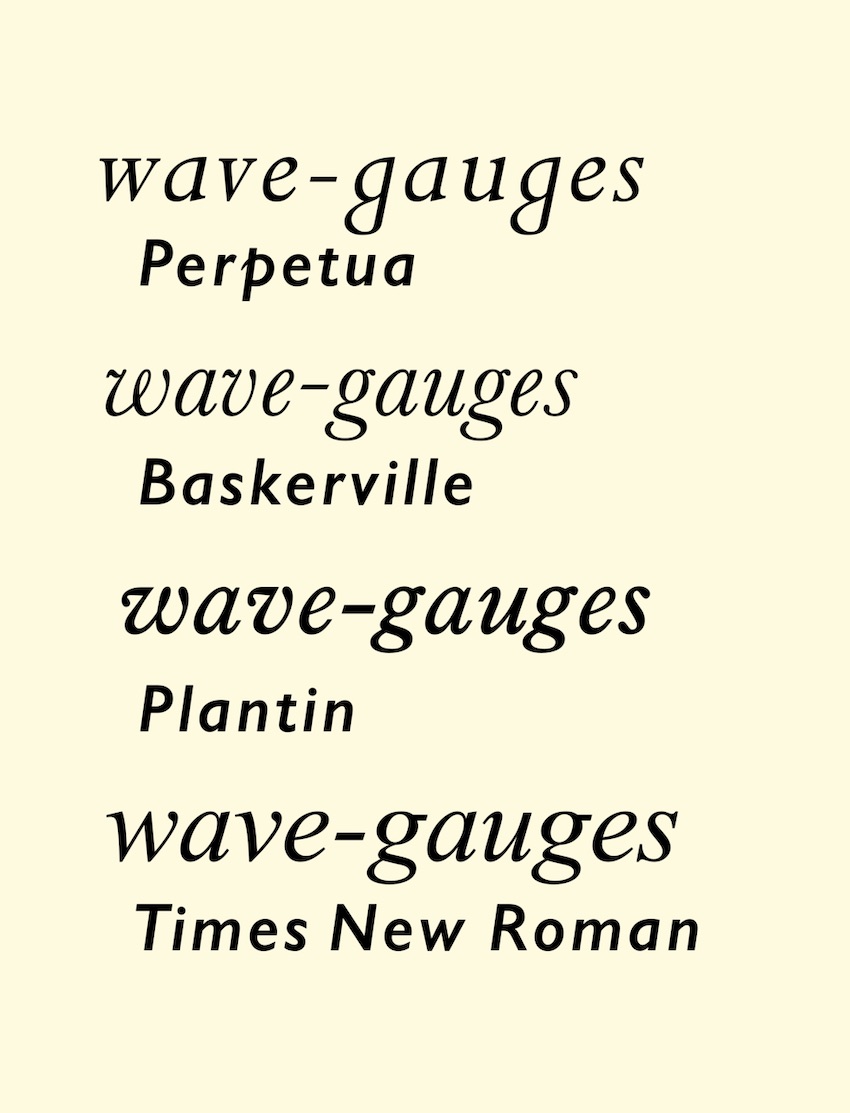
Шрифт Times New Roman: история и причины популярности
Популярность шрифтов, подобных Times New Roman, растет, и легко понять, почему. Классическое семейство шрифтов Times New Roman используется повсюду, от газет до популярного программного обеспечения, и теперь оно стало мгновенно узнаваемым.
Но то, что Times New Roman хорошо знакомо означает, что он стал чем-то вроде заурядного дизайнерского выбора. Вариант по умолчанию, но кому это нужно?
Выбирая шрифт, который содержит определенные черты Times New Roman, но также имеет собственную индивидуальность, вы получаете лучшее из обоих миров: классический стиль с современными нотками.
В этой статье мы рассмотрим шрифты, похожие на Times New Roman. Но сначала давайте коротко узнаем историю самого Times New Roman.
История Times New Roman
Семейство шрифтов Times New Roman сегодня встречается повсюду, но с чего все это началось? Впервые шрифт появился в британской газете The Times 3 октября 1932 года.
The Times поручила годом ранее полиграфической компании Monotype изменить дизайн шрифта, а дизайнер Стэнли Морисон рекомендовал более солидный и современный дизайн для замены своего предшественника 19 века. Он использовал шрифты Perpetua, Baskerville и Plantin в качестве вдохновения, но внес существенные изменения, чтобы создать уникальный шрифт, который выдержит испытание временем.
The Times продолжали использовать Times New Roman еще 40 лет, прежде чем в 1972 году придумали новый дизайн и с тех пор было еще несколько изменений. Все новые шрифты по-прежнему основаны на оригинальном дизайне Times New Roman Морисона.
С 1972 года семейство шрифтов Times New Roman начало жить собственной жизнью, получив известность далеко за пределами газетного мира. В первые дни Интернета веб-сайты могли использовать только несколько шрифтов, и Times New Roman был одним из них. Посмотрите на веб-сайт 1997 года, и, скорее всего, он использует Times New Roman.
Times New Roman также был шрифтом по умолчанию в Microsoft Word в течение многих лет, а Word был программным обеспечением по умолчанию для всех, кто создавал документы в те дни. Так Times New Roman стал стандартом для всего, от юридических документов до школьных сочинений. Это было повсюду.
В настоящее время, когда доступно так много различных вариантов, Times New Roman не так доминирует, как раньше. В наши дни дизайнеры часто уклоняются от него, считая, что это слишком примитивно, слишком скучно. И все же вы все равно увидите, что он появляется в документах и на веб-сайтах и, как вы узнаете позже в этой статье, есть несколько отличных альтернатив Times New Roman, которые можно взять, чтобы использовать его классическую привлекательность при создании дизайна со своей индивидуальностью.
Характеристики Times New Roman
Есть вопросы о семействе шрифтов Times New Roman? Вот несколько ответов на распространенные вопросы об этом популярном шрифте.
Какой тип шрифта Times New Roman?
Times New Roman — это шрифт с засечками, разработанный для хорошей читабельности в плотных газетных столбцах. Он довольно сжатый, имеет большую высоту по оси Х и короткие нижние выносные элементы. Все это позволяет легко читать даже при небольшом размере и в плотных столбцах текста.
Times New Roman — это шрифт с засечками?
Да. Он классифицируется как переходный шрифт с засечками, что означает, что он находится между старым и современным.
Times New Roman - моноширинный шрифт?
Нет. Times New Roman — это пропорциональный шрифт или шрифт переменной ширины. В моноширинных шрифтах все символы имеют одинаковую ширину — они были обычным явлением во времена пишущих машинок и на заре компьютерного кодирования. Как правило, шрифты переменной ширины, такие как Times New Roman, приятны для глаз.
Вопрос мог возникнуть, потому что Times New Roman была создана компанией Monotype. Но название не имеет ничего общего с моноширинными шрифтами.
Какие шрифты похожи на Times New Roman?
Хороший вопрос! В следующем разделе мы рассмотрим несколько примеров шрифтов Times New Roman, так что читайте дальше.
Шрифты, похожие на Times New Roman
Times New Roman — потрясающий шрифт, но на данный момент им немного злоупотребляют. Что, если вы хотите чего-то похожего, но с небольшими изменениями? Вот несколько шрифтов, как Times New Roman, которые можно попробовать.
Naia - изысканный шрифт с засечками
В этом сложном шрифте с засечками видно влияние Times New Roman, но он также имеет собственный особый стиль. Naia включает в себя все латинские символы (включая знак ударения), а также числа, специальные символы и знаки препинания. Полужирный шрифт будет отличной заменой для Times New Roman Bold.
Семейство шрифтов Sharis Serif
Шрифт Sharis Serif включает в себя некоторые черты Times New Roman, что делает его отличным для текста, где важна высокая степень разборчивости. Однако он не такой сжатый, как буквы Times New Roman, а семь различных весов позволяют создавать самые разные эффекты.
Thomas Craft: современный шрифт с засечками
Этот изысканный современный шрифт с засечками представлен в четырех различных весах, а также обычный набор глифов и неанглийских символов. Используйте его для заголовков, плакатов, брендов и других творческих задач.
Pierson: основной шрифт с засечками
Если вы ищете шрифты похожие на Times New Roman, лучше Pierson вам не найти. В нем та же классическая элегантность и неизменная привлекательность. Экспериментируйте с тремя разными весами и выбором глифов и используйте их для своих веб-макетов, упаковки и других проектов.
Семейство шрифтов Maiah Serif
У Maiah современный и минималистичный стиль, очень похожий на семейство шрифтов Times New Roman. Но у него также есть своя индивидуальность: четыре веса, прописные и строчные буквы, числа, базовая пунктуация и многоязычная поддержка. Скачайте Maiah и посмотрите, что вы можете с ним создать!
Семейство шрифтов Glamour Luxury Serif
Это шрифт с хорошим названием: он действительно передает гламур и роскошь. Он используется на страницах глянцевых журналов моды или для упаковки высококачественных продуктов. Он имеет четыре веса, а также глифы и неанглийские символы. Вы обнаружите, что цифры очень похожи на цифры Times New Roman.
Aadam: современное семейство шрифтов с засечками
Как и многие шрифты, похожие на Times New Roman, Aadam прекрасно сочетается с прописными буквами, сигнатурами или рукописными шрифтами. Его простой и минималистский стиль идеально подходит для чего-то более экспериментального. Так почему бы не скачать его и посмотреть, сможете ли вы найти идеальное сочетание?
Гарнитура Vera
А вот альтернатива Times New Roman, которая предлагает нечто немного иное. Это очень высокий и узкий дисплейный шрифт, что делает его идеальным для цепляющих заголовков в ограниченном пространстве, таких как обложки журналов и титульные листы. Можно выбрать стиль: жирный, обычный или наклонный, также Vera включает многоязычные прописные буквы, альтернативные символы, цифры и знаки препинания.
Семейство шрифтов Sandover Serif
Sandover имеет много общих черт с Times New Roman, но также выделяется сам по себе как элегантный шрифт с засечками. Вы можете выбрать один из пяти различных весов с глифами и неанглийскими символами. Используйте его для заголовков, плакатов, рекламы и многого другого.
Wild & Folk
Несмотря на название, в этом шрифте нет ничего особенного. Фактически, это стильный, элегантный шрифт, вдохновленный классическими стилями. Посмотрите на цифры, и вы увидите, что они довольно близки к числам Times New Roman. Однако Wild & Folk использует широкий спектр современных форматов шрифтов, поэтому вы можете использовать тот, который вам больше нравится.
Media Times
Из всех шрифтов, похожих на Times New Roman, которые мы рассмотрели сегодня, этот, вероятно, имеет самое большое сходство. Символы очень похожи на буквы Times New Roman, но с достаточными различиями, чтобы выделить ваш текст. Это был бы идеальный корпоративный шрифт, или почему бы не использовать его для своей газеты или журнала?
Шрифт New York
New York предлагает восемь файлов шрифтов с различными теневыми и гранжевыми эффектами, чтобы внести некоторые вариации в ваш текст. Напоминающий годы бума Нью-Йорка в начале и середине 20 века, этот шрифт с засечками отлично подходит для любого проекта в стиле ретро или винтаж.
Семейство шрифтов Wensley Modern Serif
Полужирный шрифт Wensley очень похож на шрифт Times New Roman Bold, но вместе с тем этот вариант прекрасно выделит ваш текст. Вы получите множество глифов, в том числе для неанглийских символов, а также три разных веса, многоязычную поддержку и многое другое.
Aguero Serif — чистый и элегантный шрифт
Хотя символы Aguero более вытянуты, чем в Times New Roman, связь все же видна. Однако это гораздо более яркий и необычный шрифт, поэтому он идеально подходит для логотипов, заголовков, бланков и других ситуаций, в которых вам нужен привлекающий внимание дисплейный шрифт.
Earning: альтернатива Times New Roman
Если вы ищете пример шрифта Times New Roman, который довольно близок к оригиналу, попробуйте Earning, жирный шрифт с засечками, идеально подходит для бизнеса и корпоративного использования. Однако, несмотря на название и превью, он не ограничивается бизнесом и финансами — вы можете использовать его в различных проектах.